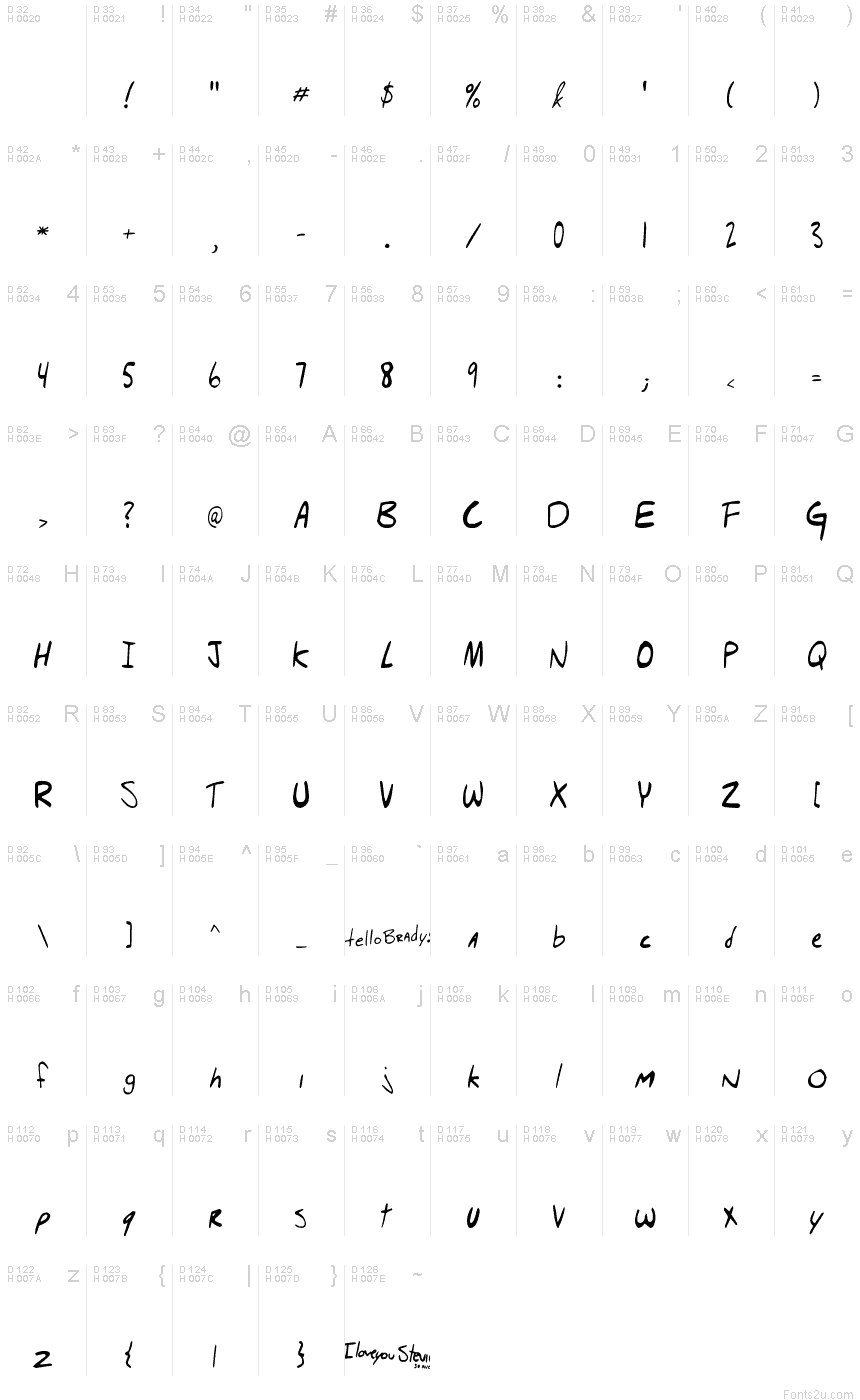
Hello Brady's Dad! je bezplatné ručně psané písmo s uvolněnou, inkoustovou energií, která připomíná rychlou poznámku nalepenou na lednici. Vysoká, lehce nakloněná písmena a silné tahy jako od štětce působí hřejivě a lidsky – jako přátelský hlas promlouvající přímo ze stránky. Písmo je ležérní, ale přitom přehledné, takže váš vzkaz zůstane na první pohled čitelný.
Hello Brady's Dad! skvěle využijete u pracovních listů pro děti, školních plakátů, narozeninových pozvánek, rodinných blogů, nadpisů ve scrapbookingu nebo hravé grafiky na sociální sítě. Tento font zdarma vynikne i na etiketách produktů nebo obalech, které potřebují osobitý, domácký nádech. Zkuste ho zkombinovat s čistým bezpatkovým písmem pro hlavní text a nechte Hello Brady's Dad! vyniknout v nadpisech, kde jeho osobitost nejlépe zazáří.